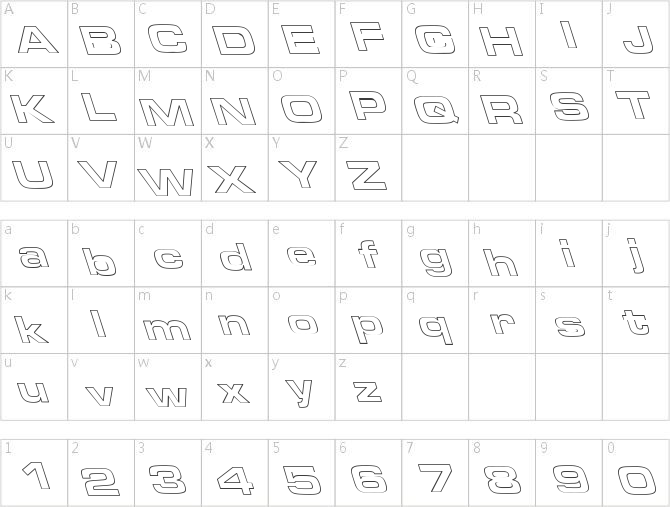
Aero Extended Hollow Lefty
Aero Extended Hollow Lefty介紹
Aero Extended Hollow Lefty字體字庫是一款讓人賞心悅目、百看不厭的英文字體,適合各類廣告和產品包裝設計應用,字體大小0.06MB,格式為ttf字體,上傳用戶是志誠設計,作者/版權方為未知